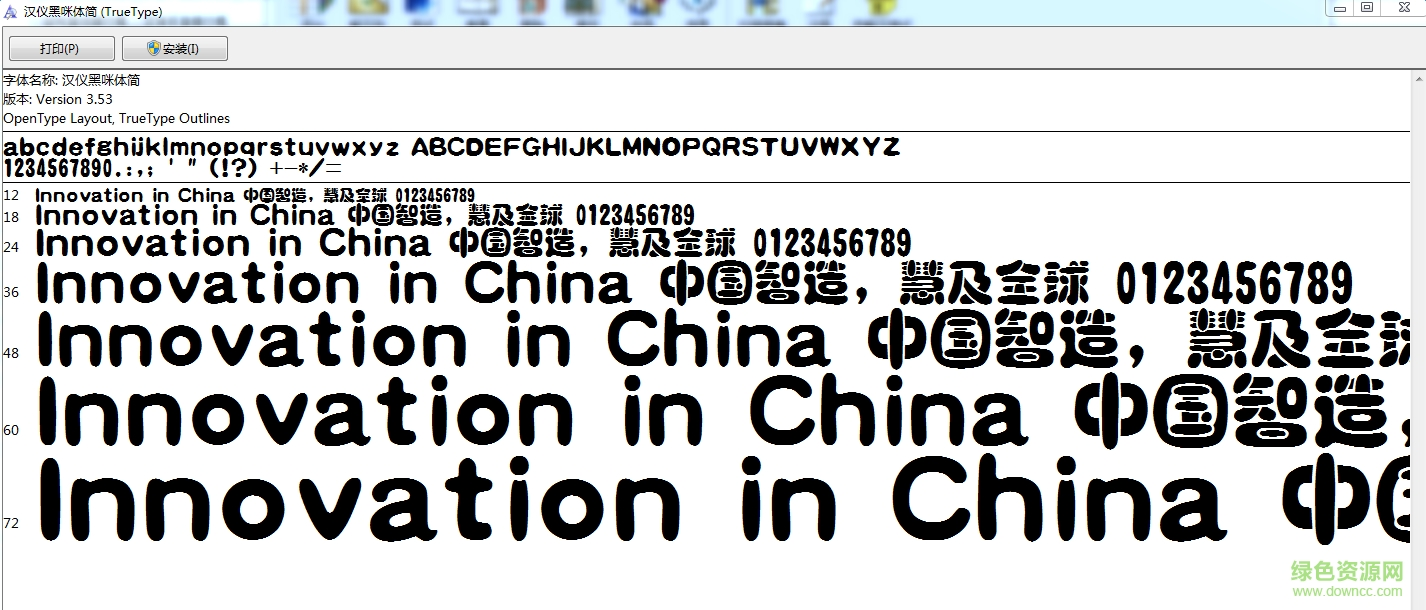
漢儀黑咪體簡(jiǎn)字體
漢儀黑咪體簡(jiǎn)字體是一款漢儀類(lèi)標(biāo)志明顯的字體軟件,黑咪體給人非常震撼醒目的感覺(jué),適用于海報(bào)廣告等設(shè)計(jì),也深受廣大書(shū)法家的喜愛(ài),還有更多好看字體盡情期待,歡迎到綠色資源網(wǎng)下載體驗(yàn)!